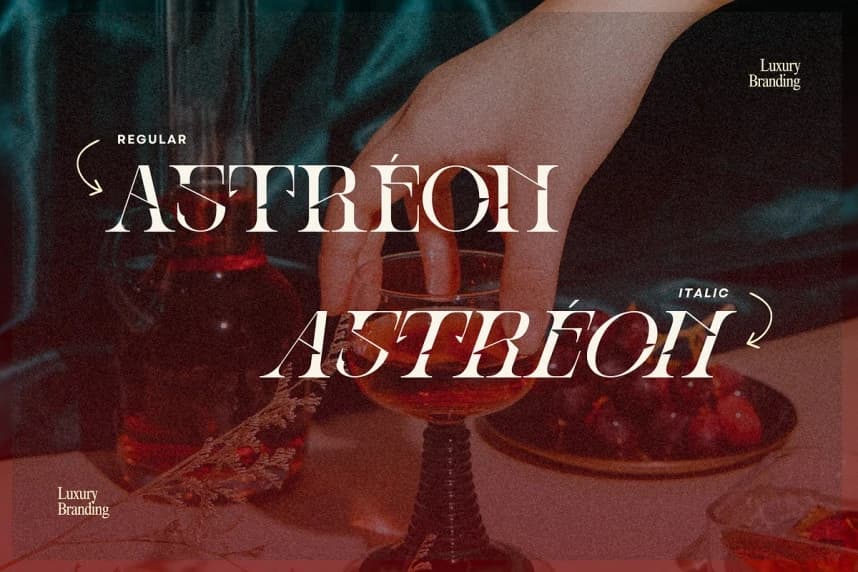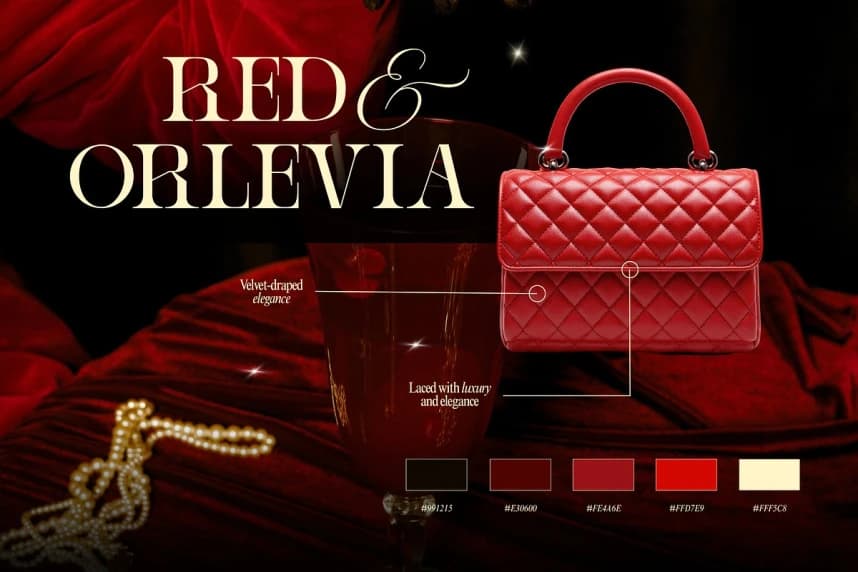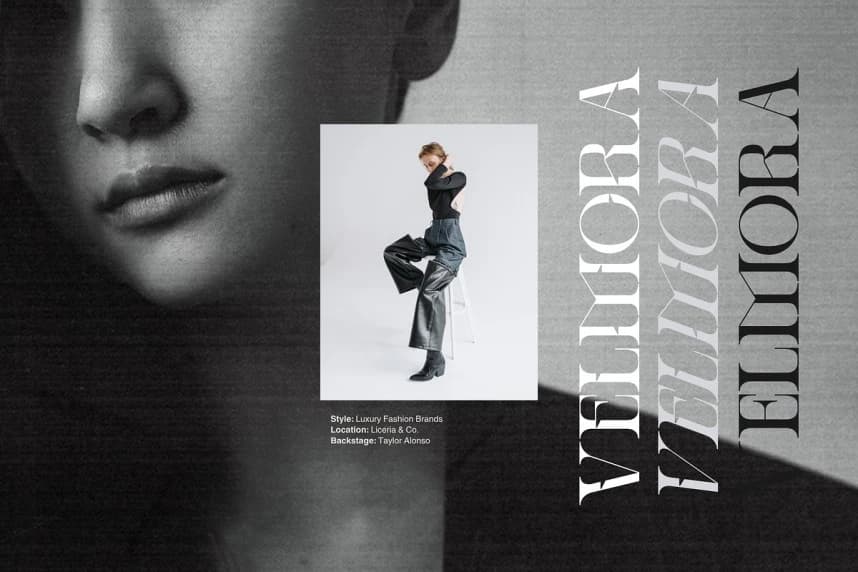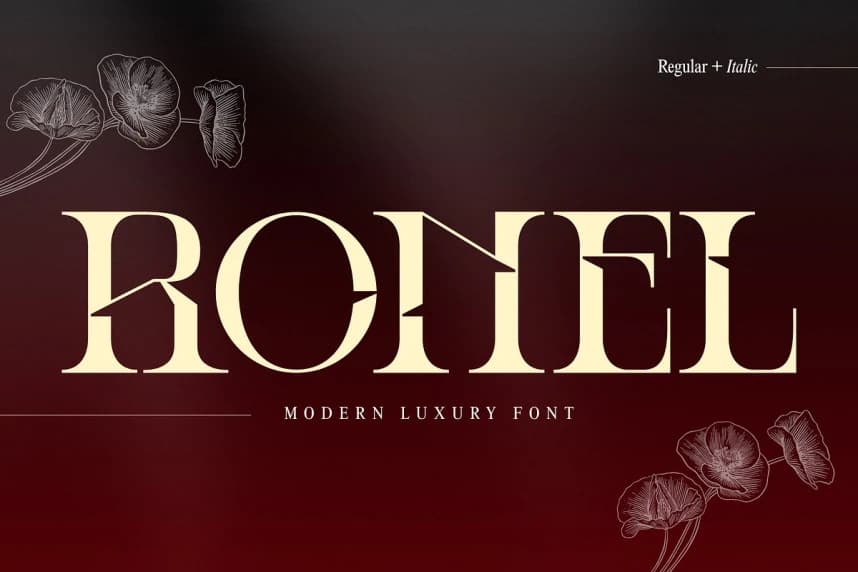
Ronel Luxury Font, her detayı zarafet ve üst düzey çekicilik sunmak üzere tasarlanmış modern, tüm harfleri büyük olan bir yazı tipidir. Regular ve Italic stillerini içeren bu yazı tipi, temiz bir yapı ile benzersiz akıcı çizgileri birleştirir ve bu sayede ona belirgin, premium bir karakter kazandırı
Ronel Luxury Font, her ayrıntıda zarafet ve üst düzey çekicilik sunmak üzere tasarlanmış modern, tamamen büyük harflerden oluşan bir yazı tipidir. Hem Regular hem de Italic stillerine sahip olan bu yazı tipi, temiz bir yapı ile benzersiz akıcı çizgileri birleştirerek ayırt edici, premium bir karakter kazandırır.